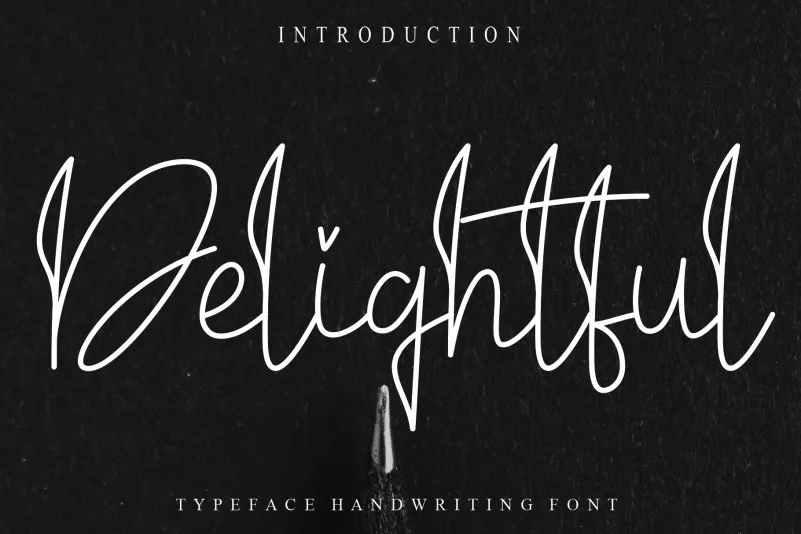
Descubra a delícia que é trabalhar com a Delightful Handwritten Font. Criada pelo designer talentoso da creativeletter, esta fonte de calligrafia traz um toque de criatividade e naturalidade para seus projetos. Seja você uma profissional ou um amante de design, você vai adorar o modo como Delightful Handwritten Font transforma qualquer projeto em algo único. Com suas letras fluidas e elegantes, ela é perfeita para personalizar anúncios, criação de conteúdo online e até mesmo sua própria identidade visual. Testemunhar a evolução da Delightful Handwritten Font é como mergulhar diretamente no mundo da arte com uma mão delicada que faz as coisas chegar à perfeição. Descubra o toque especial desta fonte de calligrafia e veja por si mesmo como ela pode transformar sua experiência criativa em algo inesquecível.